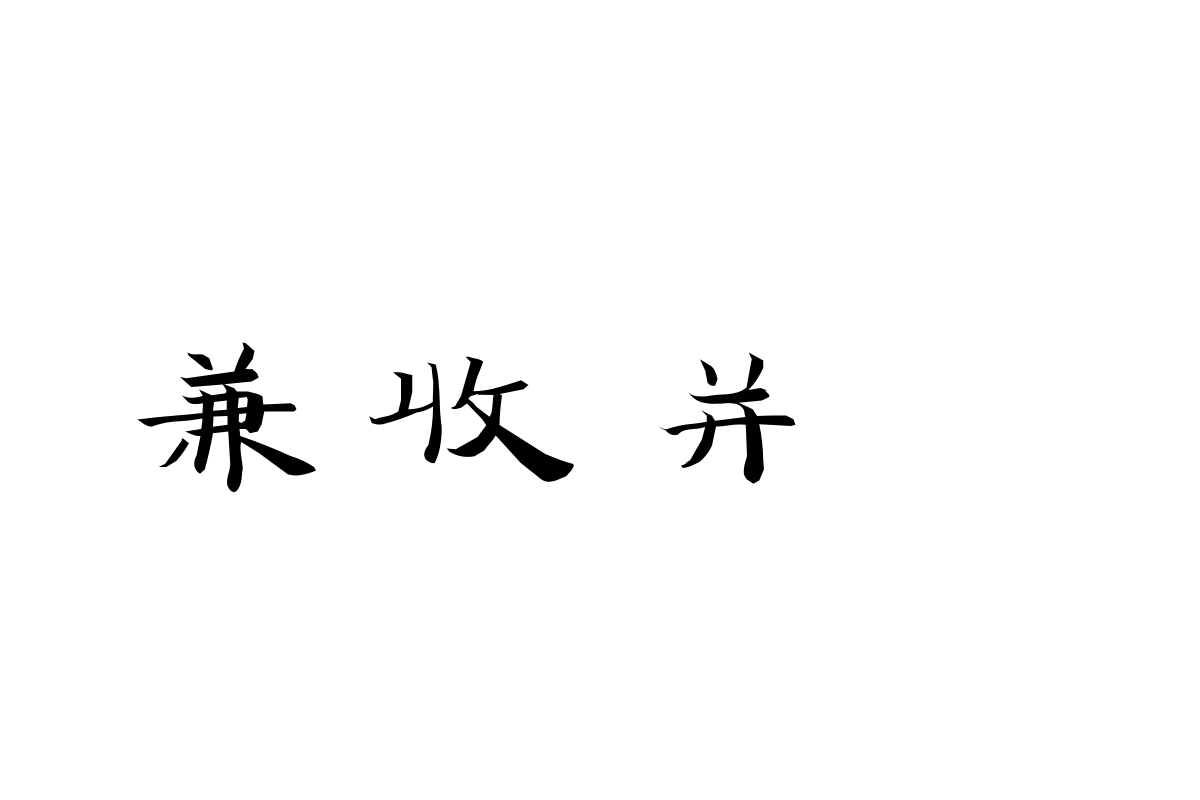
汉仪李政恩小楷简是一款专为书法爱好者设计的字体,具有独特的韵味和风格。这款字体采用了传统的小楷书写技巧,笔画流畅自然,线条清晰,给人一种宁静、优雅的感觉。同时,字体结构紧凑,字形规整,易于书写和阅读。
汉仪李政恩小楷简的字体特点如下:
1. 笔触流畅:这款字体的笔画线条流畅自然,没有过多的顿挫和转折,给人一种轻松愉悦的书写体验。
2. 字形规整:字体结构紧凑,字形规整,每个字的笔画都按照一定的顺序排列,使得整体效果更加协调统一。
3. 易于书写:由于字体结构简单明了,笔画较少,因此非常适合初学者学习和练习,可以快速掌握书写技巧。
4. 适用于多种场景:无论是用于个人日记、书信还是作为艺术作品,汉仪李政恩小楷简都能展现出其独特的韵味和风格。
总之,汉仪李政恩小楷简是一款适合书法爱好者的字体,它具有流畅自然的笔触、规整的字形和易于书写的特点,是学习和欣赏书法的理想选择。